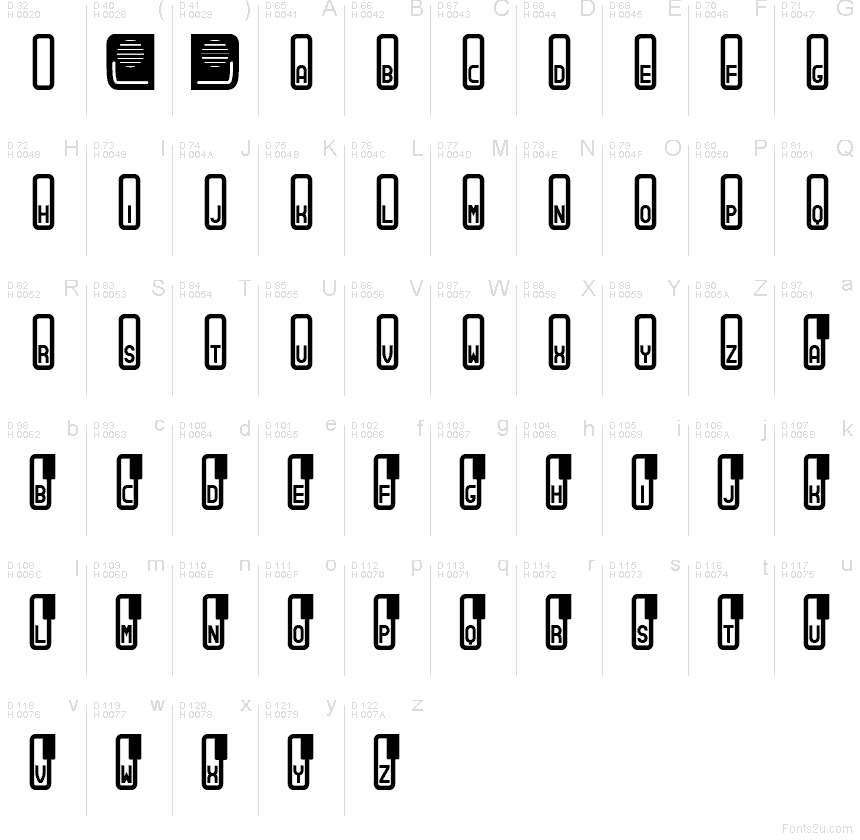
Yamaha Extravagant Regular
Yamaha Extravagant od Vladimira Nikoliče je bezplatný font typu display, který mění písmena v kompaktní rytmus klaviatury. Opakující se vzor černo-bílých kláves dodává designu jeho charakter, zatímco tvary jednotlivých písmen zůstávají úhledně zasazeny do této hudební mřížky, místo aby působily jako běžné dekorativní písmo.
Díky tomu je přirozenou volbou pro letáky hudebních škol, plakáty na výuku hry na klavír, názvy hudebních akcí, obaly alb a grafiku pro YouTube spojenou s klavírní nebo popovou produkcí. Protože motiv klaviatury prostupuje celým návrhem, skvěle poslouží i pro loga, samolepky a příspěvky na sociálních sítích, kde téma musí být okamžitě čitelné bez dalších ilustrací.